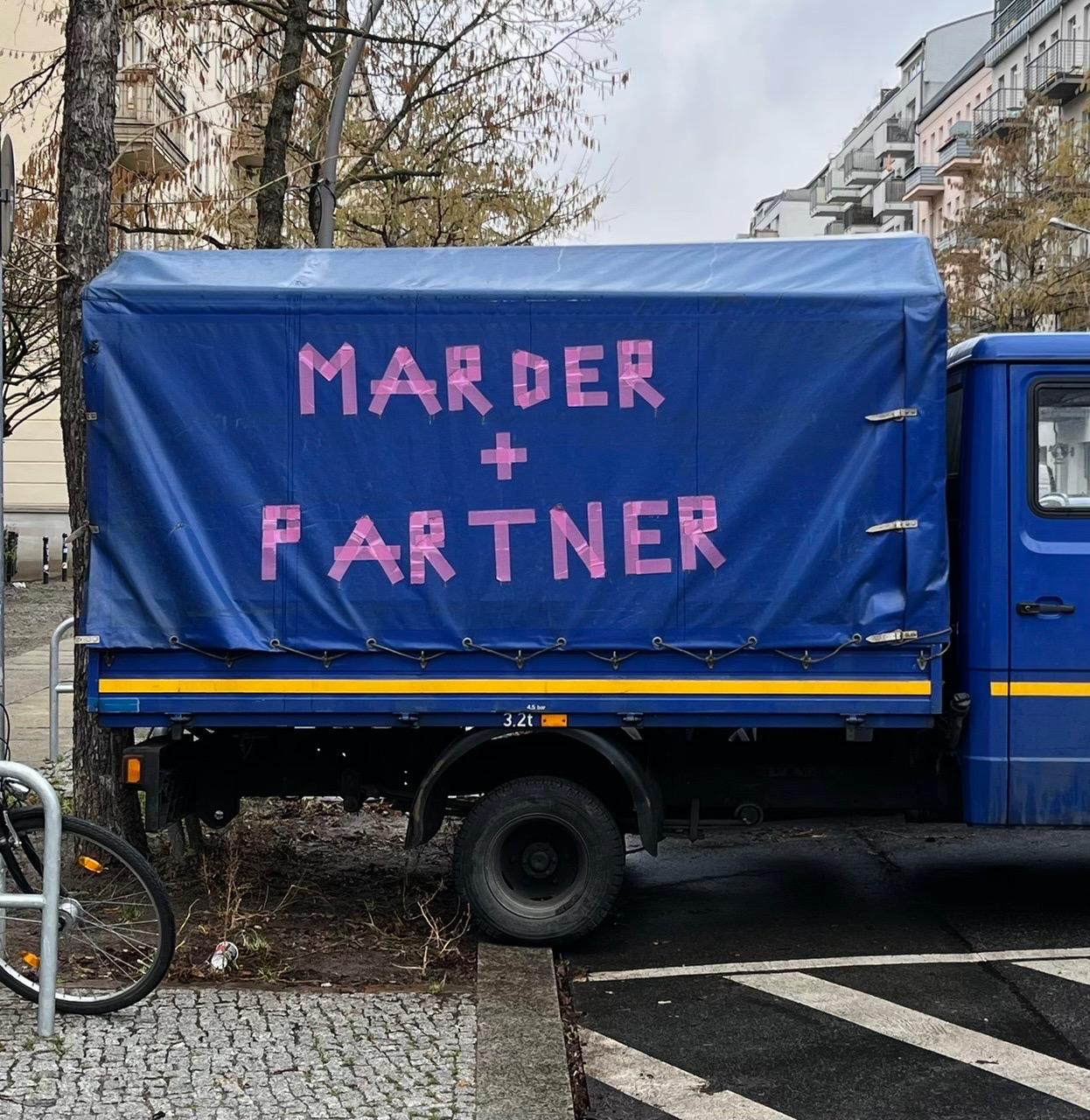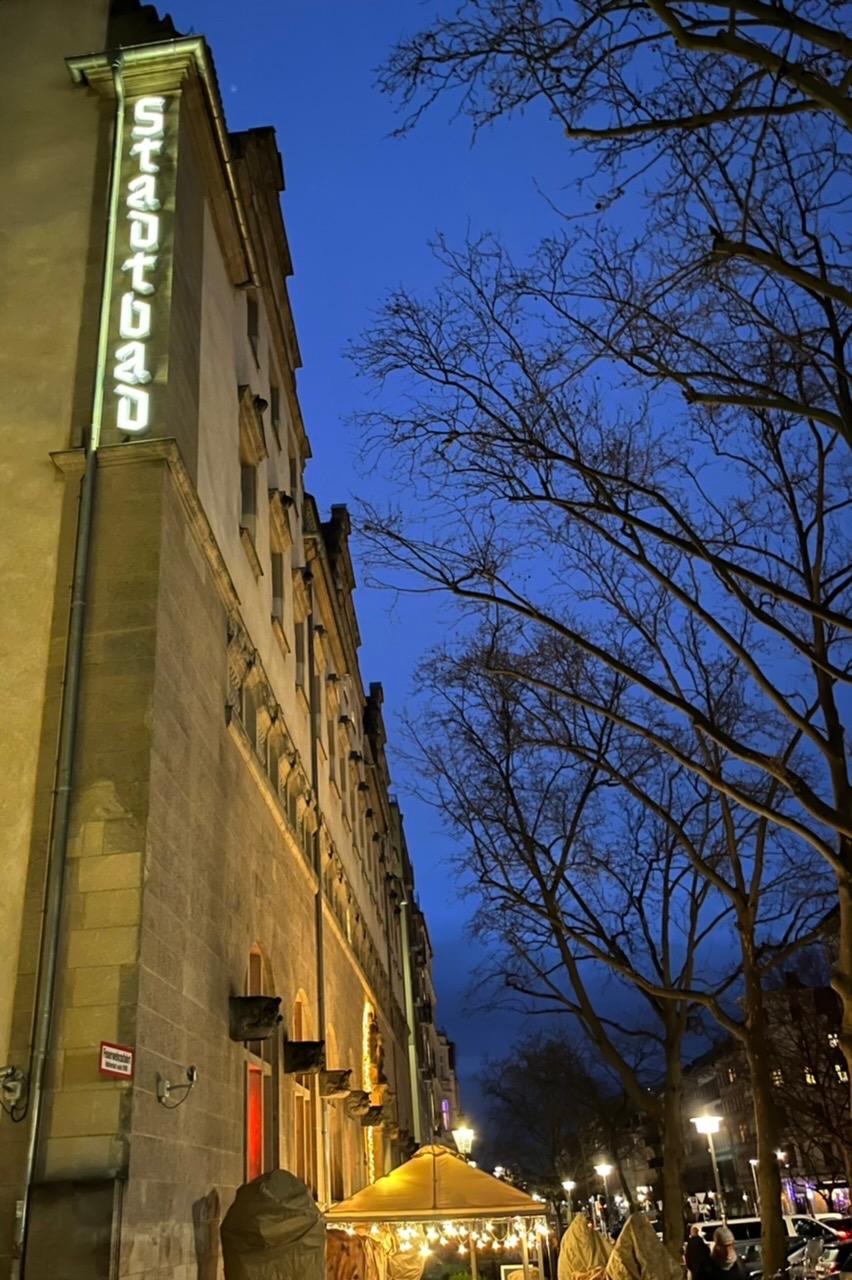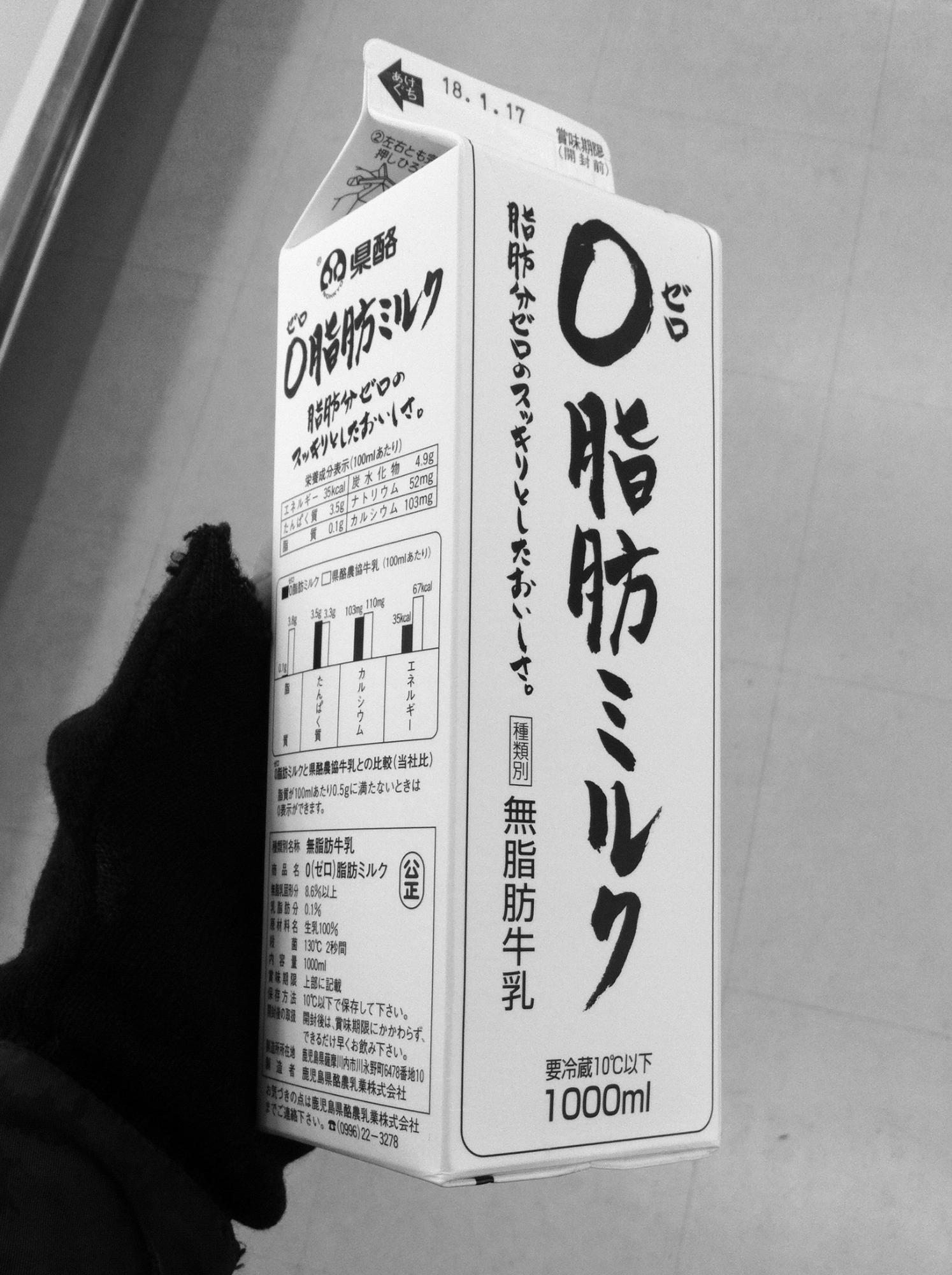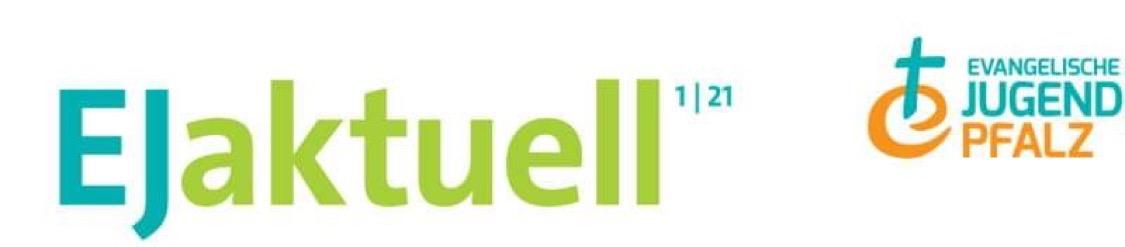
Der Auftritt von Marder + Partner ist das Ergebnis einer tiefgreifenden, nachhaltigen Umarbeitung des bisherigen Erscheinungsbild des Berliner Unternehmens. Das modernisierte Corporate Design stammt aus der Feder der mehrfach ausgezeichneten Agentur Tesa & Krepp. Ein Bestandteil des neuen CD ist die Hausschrift, die sich auf der Höhe der Zeit präsentiert: ein Colorfont mit vielen Alternativglyphen.
Japan, 2018. (Die Kalligrafie ist schwarz auf weiß.)
Ich war erst irritiert, aber man schreibt dort das Datum umgekehrt: Jahr. Monat. Tag.
Schön, wie sie extra »Zero« neben die Null schreiben – nicht, dass man das für Zen-Fett-»Milk« hielte …
Gemutmaßt, gewusst oder kannst du japanisch? Wäre mir gar nicht aufgefallen …
Katakana und Hiragana kann ich immer noch ganz gut lesen, Kanji lese ich notgedrungen immer »chinesisch« im Kopf, da das letzte Mal, dass ich Japanisch können musste, 27 Jahre her ist.
Was soll man dazu sagen? Außer vielleicht: »Lorem ipsum dolor sit amet, consectetur adipiscing elit, sed do eiusmod tempor incididunt ut labore et dolore magna aliqua. Ut enim ad minim veniam, quis nostrud exercitation ullamco laboris nisi ut aliquip ex ea commodo consequat. Duis aute irure dolor in reprehenderit in voluptate velit esse cillum dolore eu fugiat nulla pariatur.«
Ich steh jetzt etwas auf dem Schlauch. Geht es darum, dass man beim flüchtigen Lesen Ejaku… (wie in Ejakulat oder Ejakulieren) statt EJaktuell aufschnappt?
Es geht tatsächlich um das ejaktualisieren – es hätte auch in die Schwierige-Wörter-Ecke gepasst. Es hätte auch zu den Designer-Fundstücken gepasst.
Ich habe jetzt von Lesetheorie nicht viel Ahnung, aber zumindest meinem Hirn liegt es näher, Buchstabenansammlungen als Wörter zu interpretieren, als der farblich kodierten Trennung Beachtung zu schenken. Wenn ich da kein Sonderling bin, fehlt da ein trennender Abstand. Zusätzlich zum Farbunterschied.  Aber vielleicht irre ich auch und ich bin tatsächlich komisch bei der Verarbeitung von Glyphen.
Aber die Zeitschrift richtet sich an eine ganz andere Generation, vielleicht ist es auch nur mein alter, versauter Denkapparat. Und die Kenntnis von Vokabeln ex und iac*
Lach – ein typografischer Rohrschachtest! ;-)
Aber im Ernst: Ich empfinde das auch als Freudsche Fehlleistung. Und im kirchlichen Kontext irgendwie gleich doppelt … Ich meine übrigens mich zu erinnern, dass wir das Wort/Thema hier im Forum vor langer Zeit schon mal am Wickel hatten, kann das sein?
Rorschachtest — Auf Messen hat meine Kollegin die Broschüren mit dem Aufdruck ANSICHTSEXEMPLAR immer so übereinander geschoben, dass nur die drei Buchstaben SEX zu lesen und die anderen verdeckt waren. Sie war der Meinung, dass dieser kleine Trick mehr Besucher anlocken würde.
So tief in die Psyche der Menschen denke ich muss man da gar nicht einsteigen. “EJaktuell" hat sich im Hirn nicht abgespeichert (wenn man das Magazin noch nie zu Gesicht bekommen hat) also liest man wohl erstmal das was dem am nächsten kommt (bis man ob innerer Widerspüche nochmal genauer hinschaut).